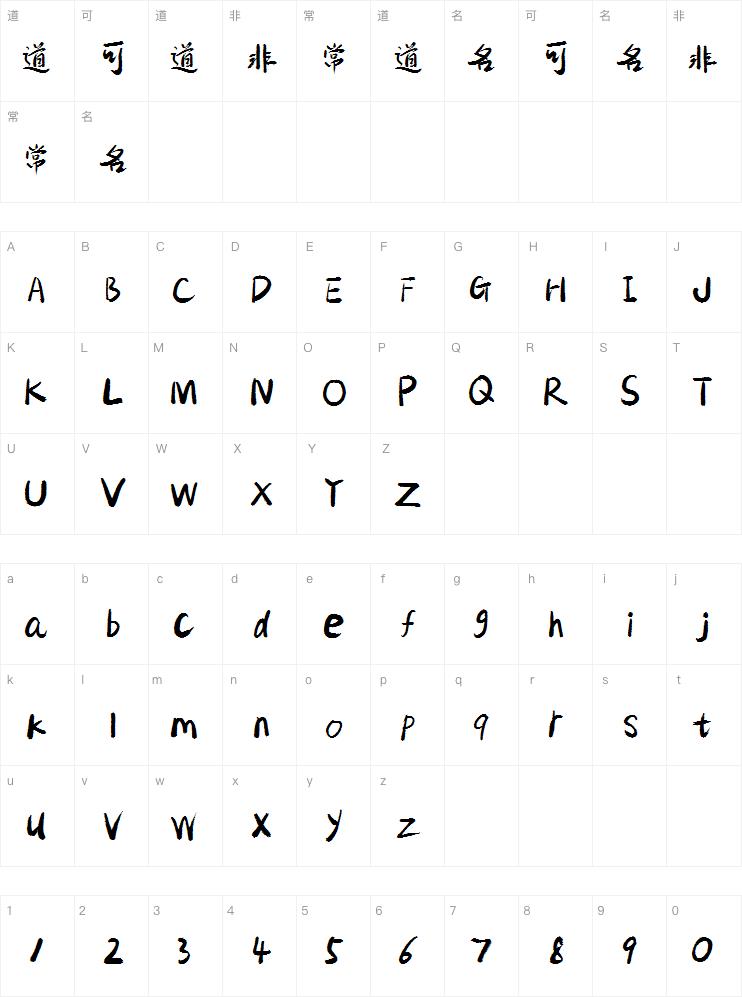
包参谋慧庭手写体是由 包参谋品牌设计 推出的一款创意书法字体。笔画飘逸洒脱,极具个人色彩。本款字体可应用于需要展示传统文化底蕴的场合,适合作为大标题字体使用。可适用于广告、包装、幻灯片演示、影视剧等场景下的标题字应用。 免费商用范围: 海报设计:海报设计用字(包括:易拉宝、背景板、海报喷绘、促销单页等) 包装设计:实物包装设计用字(包括:食品、日用百货、办公文具、五金交电、电脑数码、光盘盘面等) 宣传册设计:宣传册设计用字(包括:宣传册、楼书、说明书等) 办公设计:办公文档设计用字(包括:PPT、工作汇报、商业提案、策划案等) 平面广告设计:平面广告设计用字(包括:报纸广告、杂志广告等) 户外广告设计:户外广告设计用字(包括:灯箱广告、车身广告、楼宇广告、立柱广告、站台广告等) 转售品设计:转售品设计用字(包括:字帖、手机壳、贺卡、明信片、日历、杯子、T恤等) 影视作品设计:影视作品设计用字(包括:电影、电视剧、专题节目、滚动式影视节目等) 影视广告设计:影视广告设计用字(包括:电视广告、电影广告、短视频广告、宣传片等) 网络广告设计:第三方网络平台设计用字(包括:百度、搜狗、360、头条、淘宝、Google、Bing等) 网站设计:网站、H5应用或小程序设计用字(包括:UI、插图、广告等) 电商网店设计:第三方电商网店设计用字(包括:淘宝、天猫、京东、拼多多、亚马逊、eBay、Shopify等) 自媒体设计:自媒体设计用字(包括:微博、微信、公众号、头条、抖音、快手、Facebook、Twitter等) VI设计:VI设计用字(包括:标准字、导视手册、企业手册等) 网店设计:商标设计用字(包括:企业或产品的徽标、商标、注册商标等) 出版物设计:出版物设计用字(包括:图书、配套手册、音像制品、内部刊物、报纸、杂志、学会会刊、年度报告等) 禁止商用范围: 于各类嵌入式应用:各类嵌入式应用(包括:应用程序iOS、Android、HarmonyOS、Windows、macOS、电子屏显、电子辞典、打印机、机盒、导航仪、SoC芯片、网页、H5应用、小程序、音像制品、电子图书、电子报刊、电子文档、电子课件等嵌入)